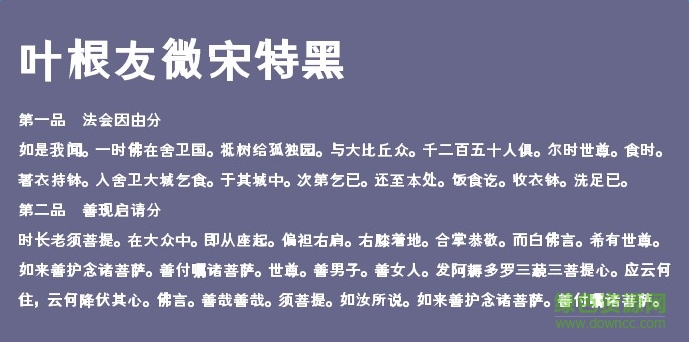
叶根友微宋特黑字体是一款粗犷超黑风格字体软件,微宋特黑体是微黑系列中比较实用的一款字体,字体笔画铿锵有力,整体效果十分醒目,适用于各大广告标题的书写,还有更多好看字体欢迎来绿色资源网下载体验!
叶根友微宋特黑字体是一款以微宋字体为原形所设计的中文字体,此款字体字形笔画均衡,识别性强,端正大方,整体风格出色。该字体适用于微宋设计、创意设计、艺术设计等方面!
经小编测试使用,字体非常粗黑,十分醒目,用于聊天搞笑别有一番韵味,整体效果好看,文雅性十足,非常适合装逼哦!!